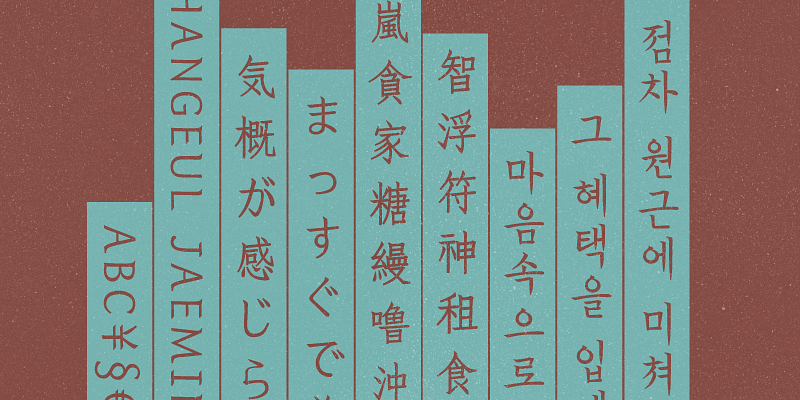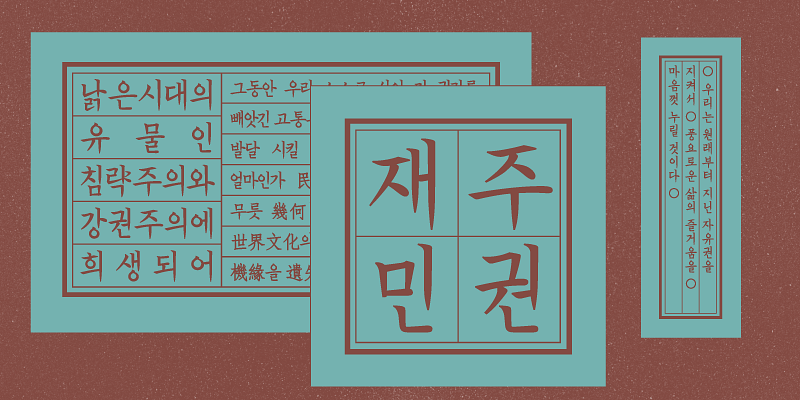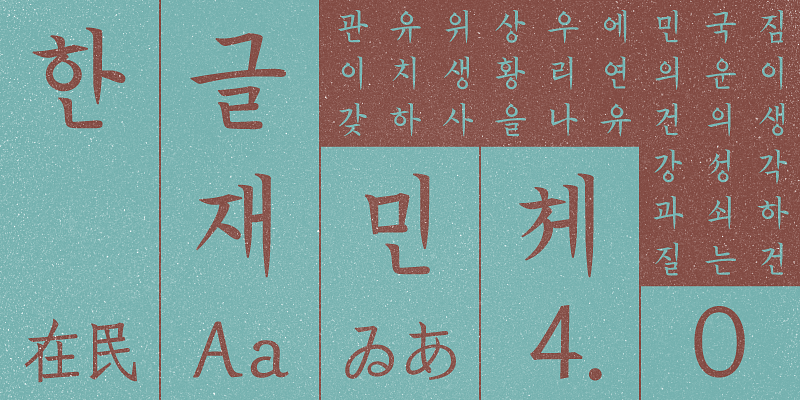
「HangeulJaemin」臣民の健康と幸福に深い関心を寄せていた大韓帝国の順宗皇帝が 1908 年に発布した勅令をルーツとするオープンソースフォント (OFL) です。このフォントはこの勅令の筆跡をベースにデザインされています。
2023 年に「HangeulJaemin 4.0」として再登場したこのフォントには、中国の日常生活でよく使われる標準的な簡体字と繁体字に加え、日本語の漢字、ひらがな、カタカナを追加して拡張されました。「HangeulJaemin 4.0」は、2,350 のハングル文字、95 の欧文文字、5 つの欧文合字、13,083 の中国語文字、198 のガーナ文字、522 の特殊文字を誇る、汎用性の高いデジタルフォントです。ハングルと英文字、中国語の簡体字と繁体字、日本語の文字にわたって一貫したデザイン表現を実現します。